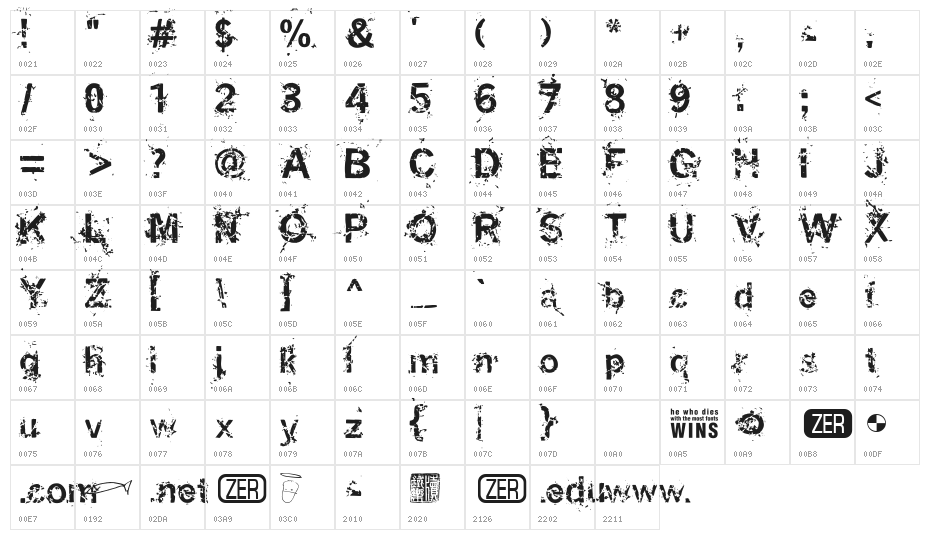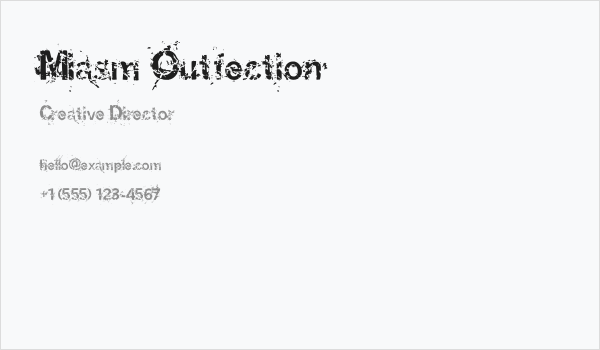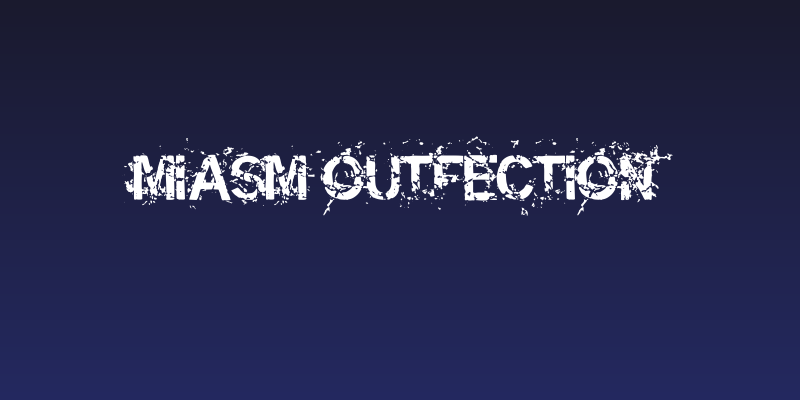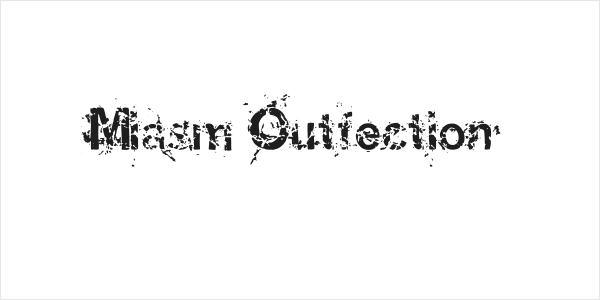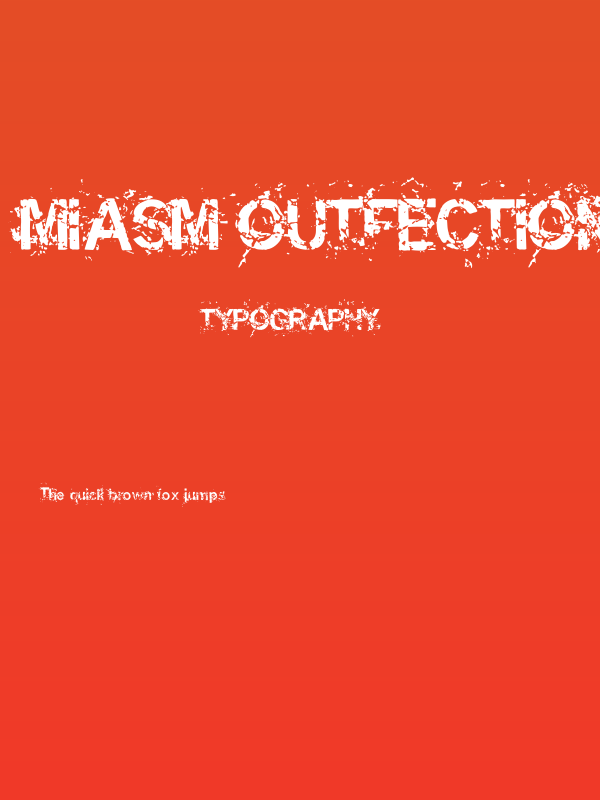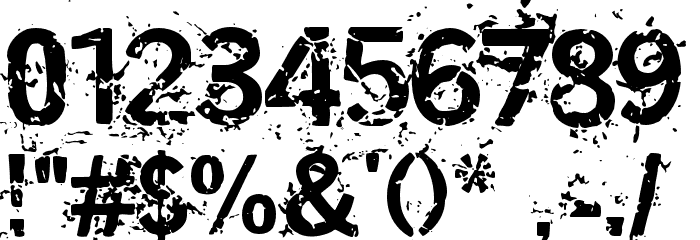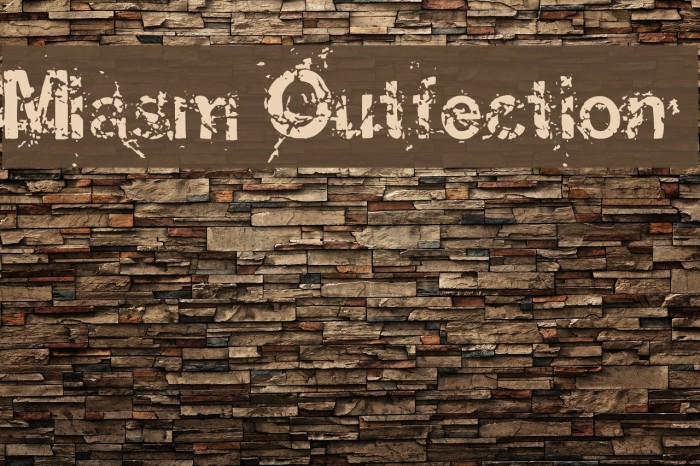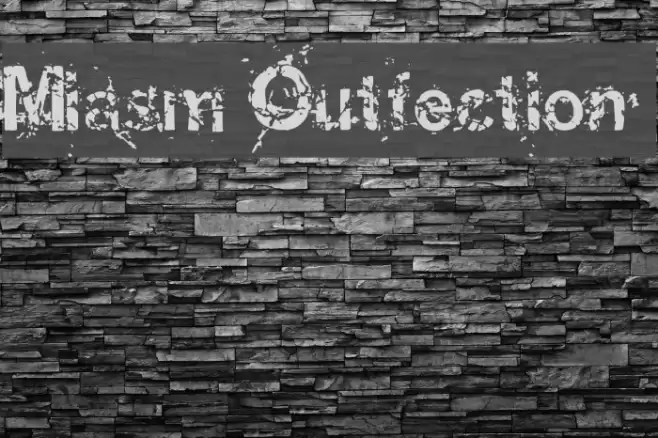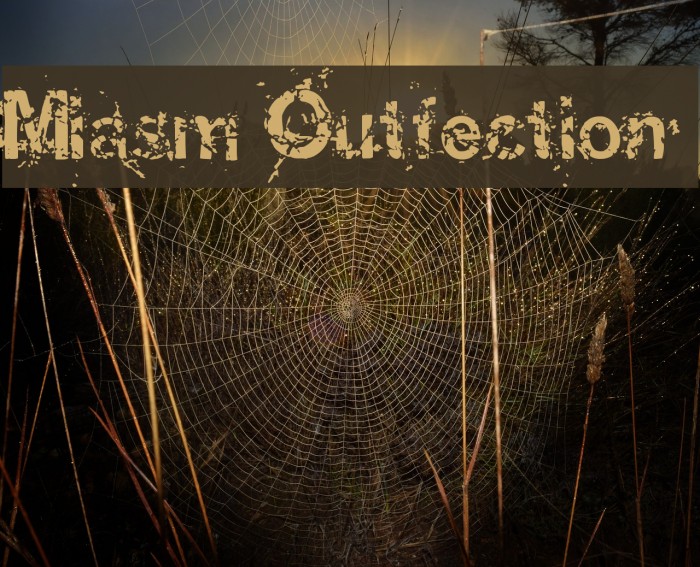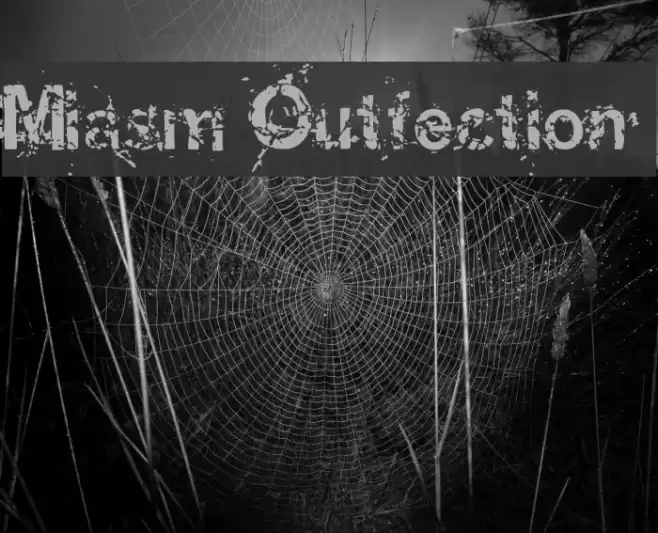
Miasm Outfection Font
✎ Distorted Eroded
| Style général | Grunge, Urban, Edgy |
| Projets proposés | Ideal for music album covers, streetwear branding, event posters, or any project needing a bold, edgy aesthetic. |